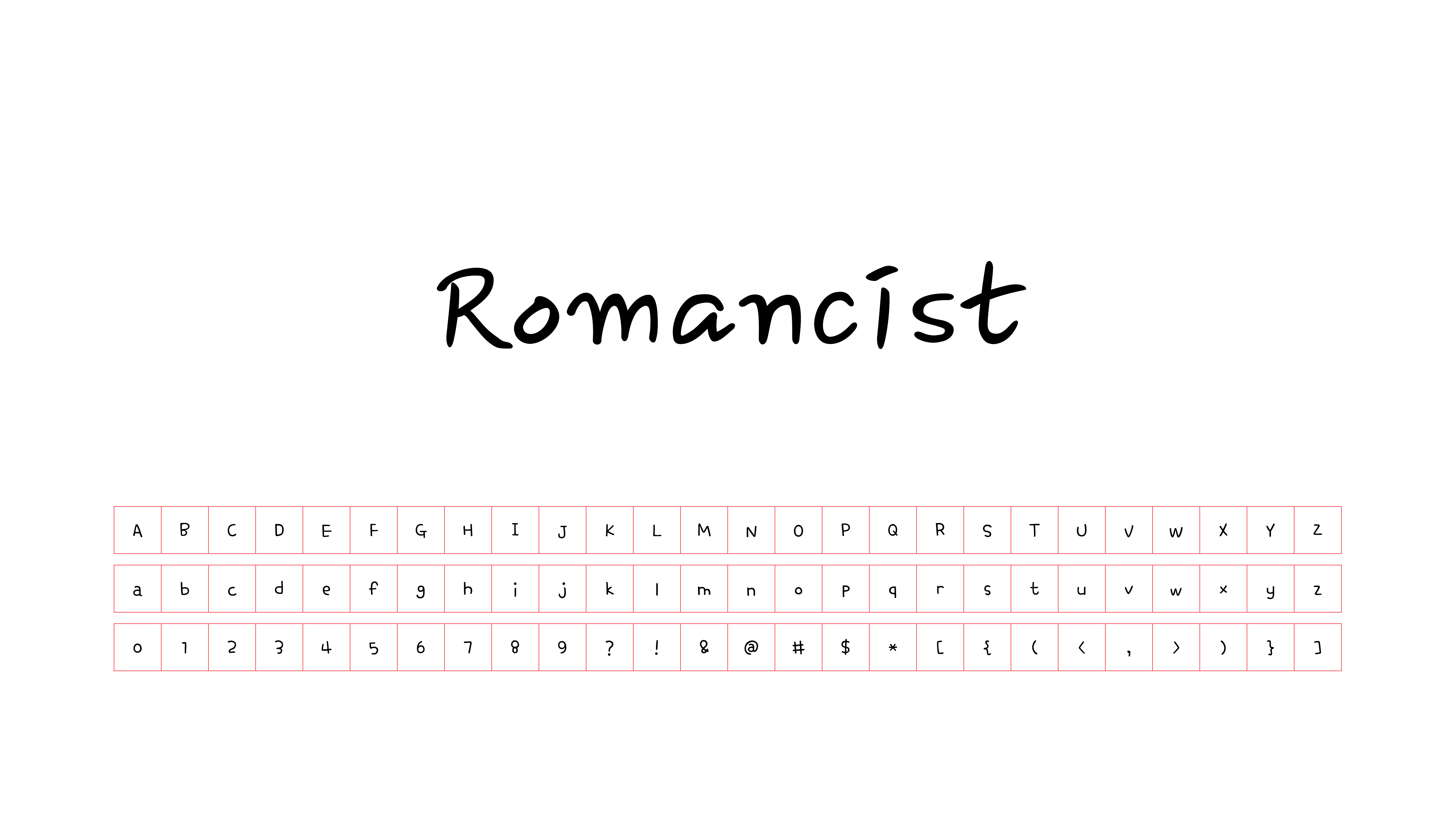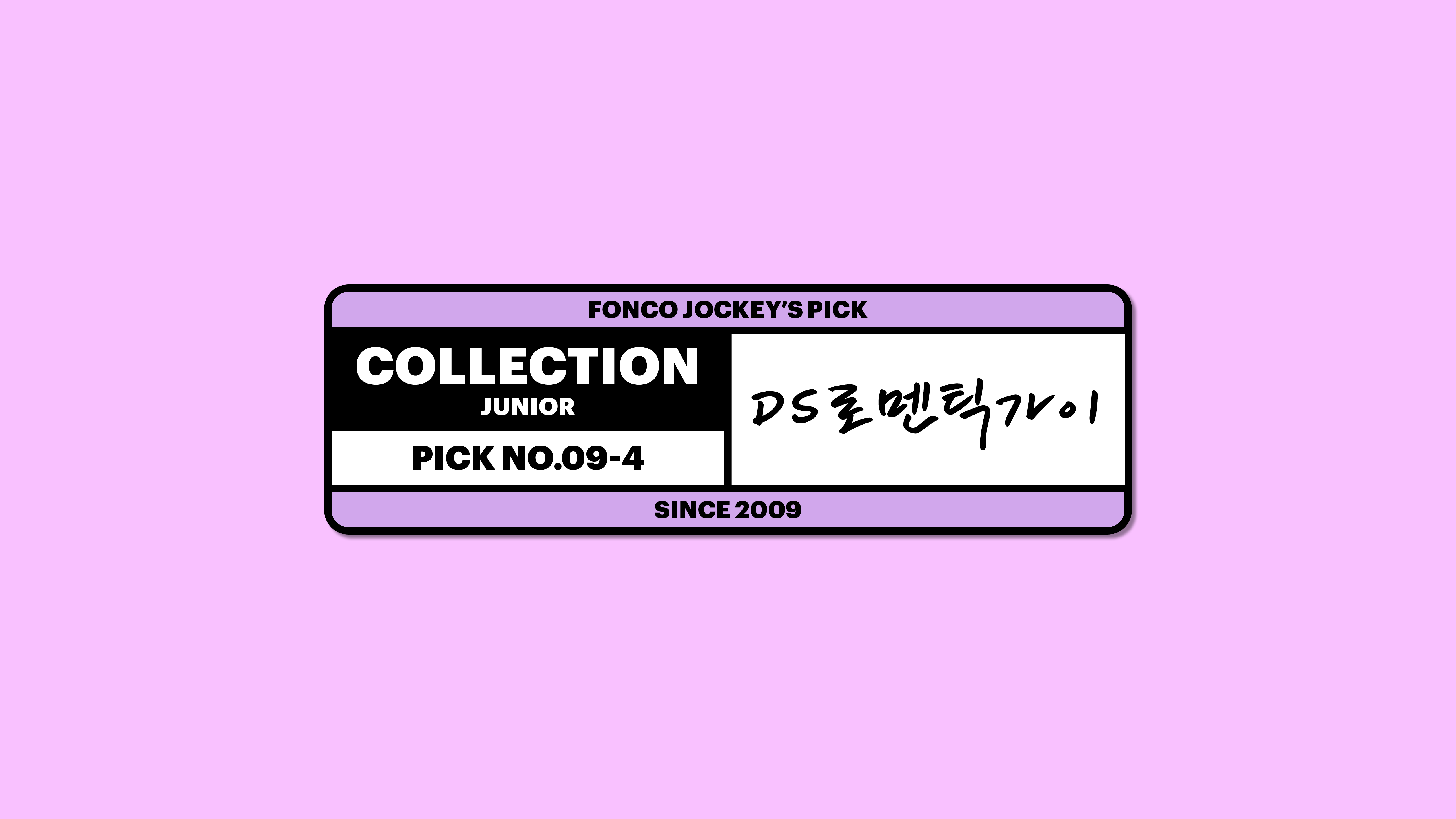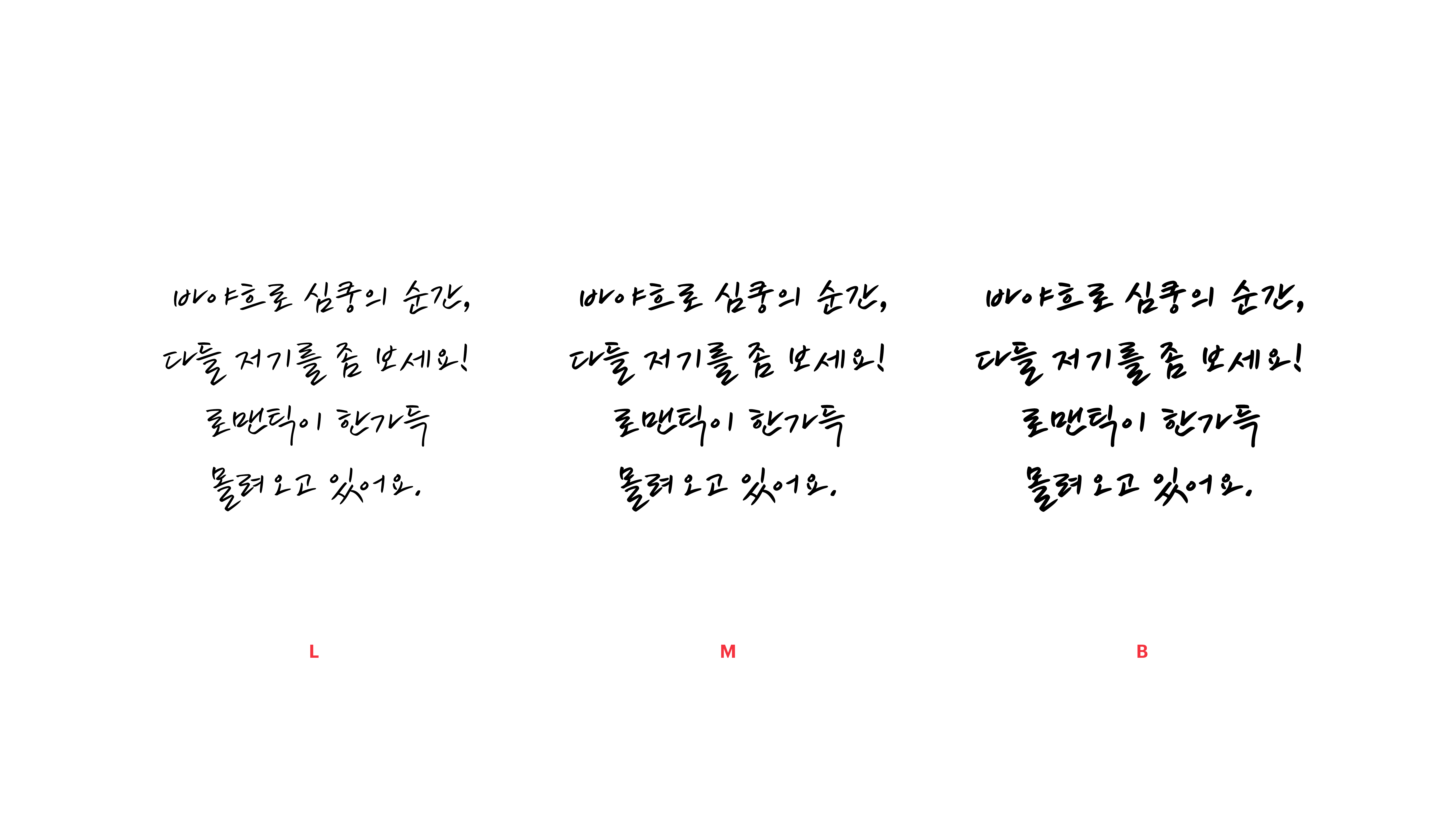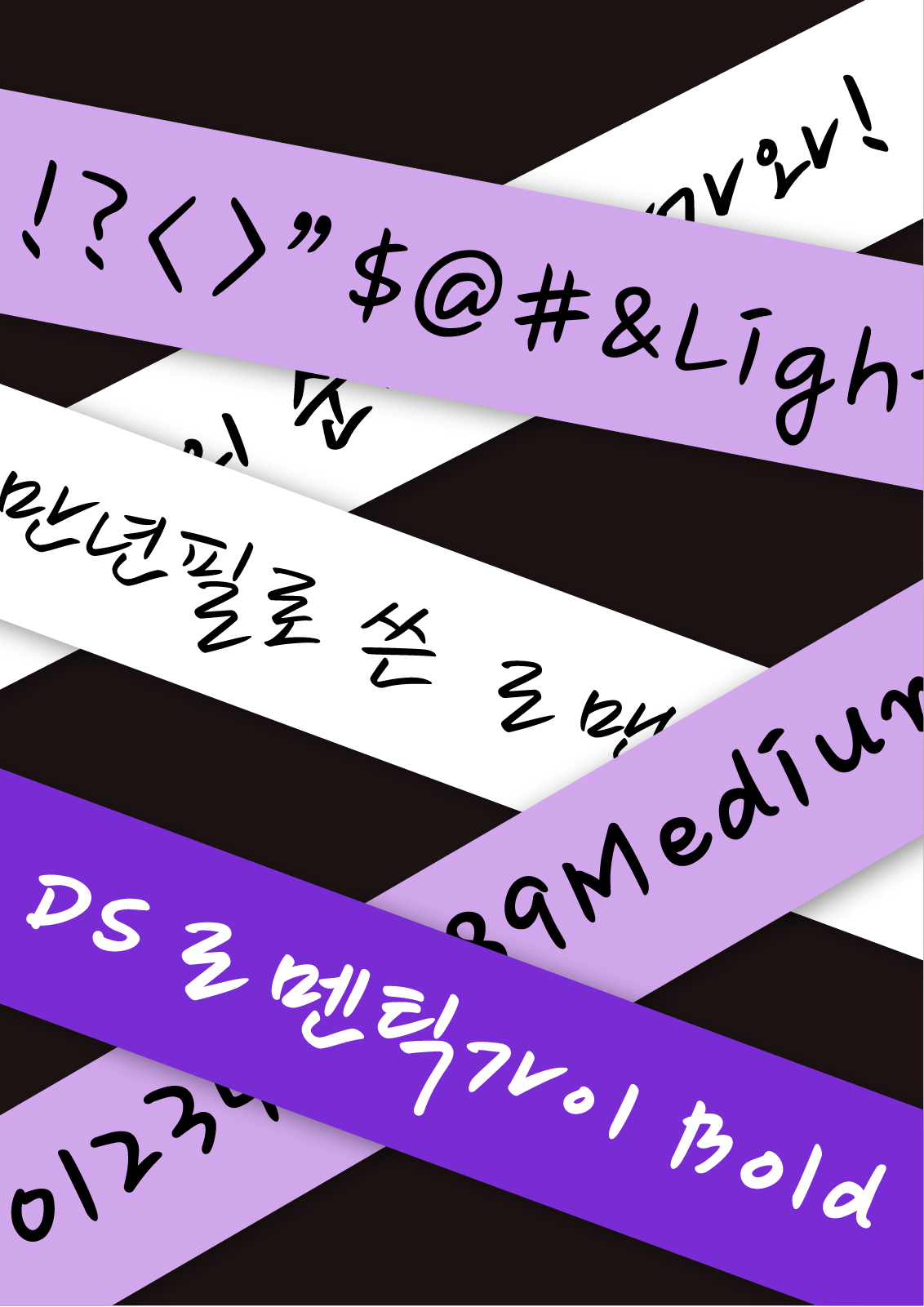
DS로멘틱가이
Yoon DS로멘틱가이
로맨틱은 달콤하고 말랑말랑한 것인 줄만 아셨다고요? 그럴 리가요! 사람마다 로맨틱을 느끼는 순간도 천차만별이랍니다. 만년필로 휘갈겨 쓴 듯한 이 거친 펜글씨 폰트를 좀 보세요. 바야흐로 심쿵의 순간, 다들 저기를 좀 보세요! 로맨틱이 한가득 몰려오고 있어요.